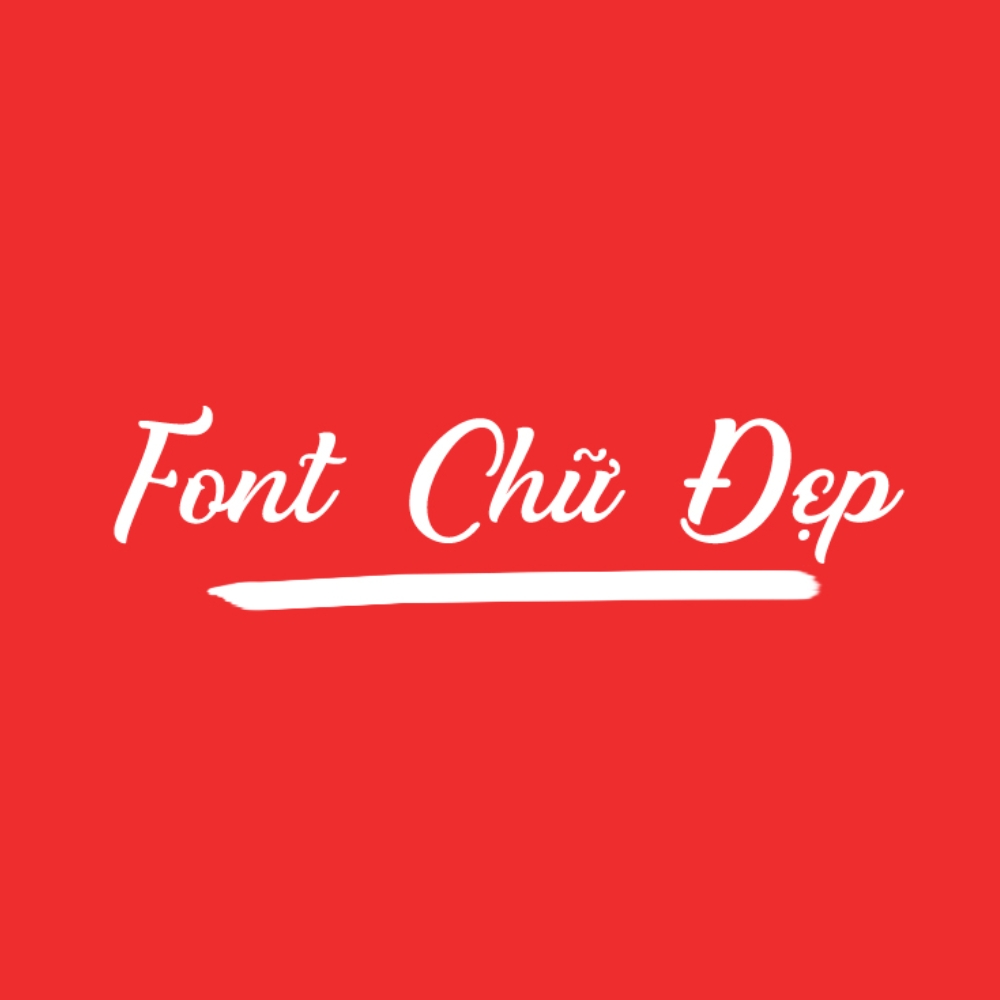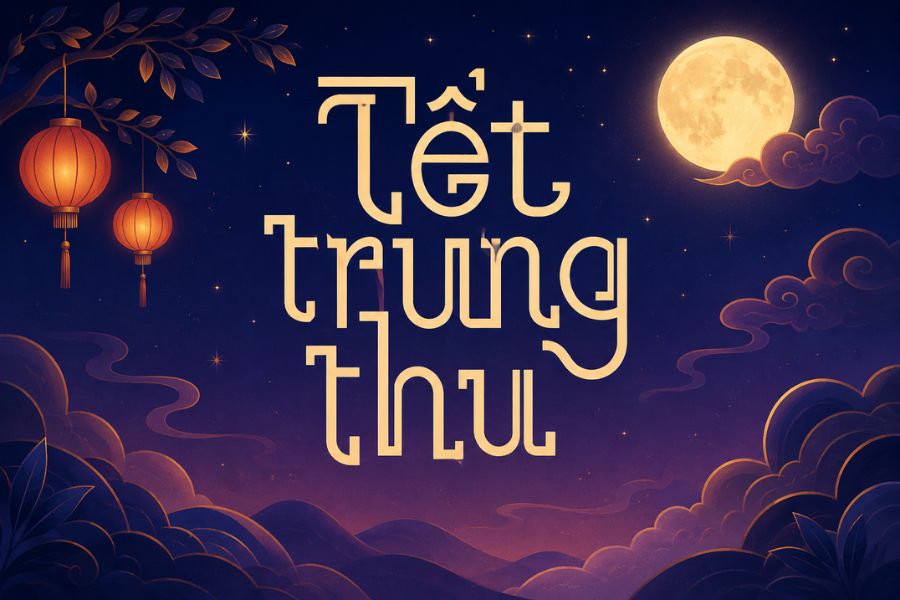
Trong các buổi báo cáo dự án hay thuyết trình ý tưởng kiến trúc, việc lựa chọn font chữ đóng vai trò quan trọng trong việc truyền tải thông tin và duy trì sự chú ý của người xem. Một bộ font chữ đẹp Powerpoint không chỉ giúp trang slide trở nên thẩm mỹ mà còn thể hiện sự chuyên nghiệp và chỉn chu của người trình bày.
Font chữ đẹp Powerpoint – Chìa khóa cho bài thuyết trình lôi cuốn
Khác với các văn bản in ấn thông thường, font chữ thuyết trình đẹp cần đáp ứng được khả năng hiển thị rõ nét từ khoảng cách xa và ổn định trên nhiều thiết bị trình chiếu. Việc sử dụng các bộ font đã được Việt hóa giúp loại bỏ tình trạng lỗi dấu thanh, đảm bảo nội dung tiếng Việt luôn mạch lạc và dễ tiếp nhận. Sự đa dạng từ các dòng font không chân hiện đại đến các dòng script nghệ thuật giúp bạn linh hoạt thay đổi phong cách phù hợp với từng chủ đề báo cáo cụ thể.
Bên cạnh yếu tố dễ đọc, font ppt đẹp còn góp phần định hình cảm xúc cho người xem. Ví dụ, các font chữ vuông vức mang lại cảm giác vững chãi, tin cậy cho các bản kế hoạch thi công, trong khi các font bo tròn lại tạo sự gần gũi cho các dự án cộng đồng. Việc chuẩn bị hồ sơ bài bản với hệ thống kiểu chữ đồng nhất sẽ giúp nâng cao hiệu quả tương tác và thuyết phục chủ đầu tư trong các buổi làm việc trực tiếp.
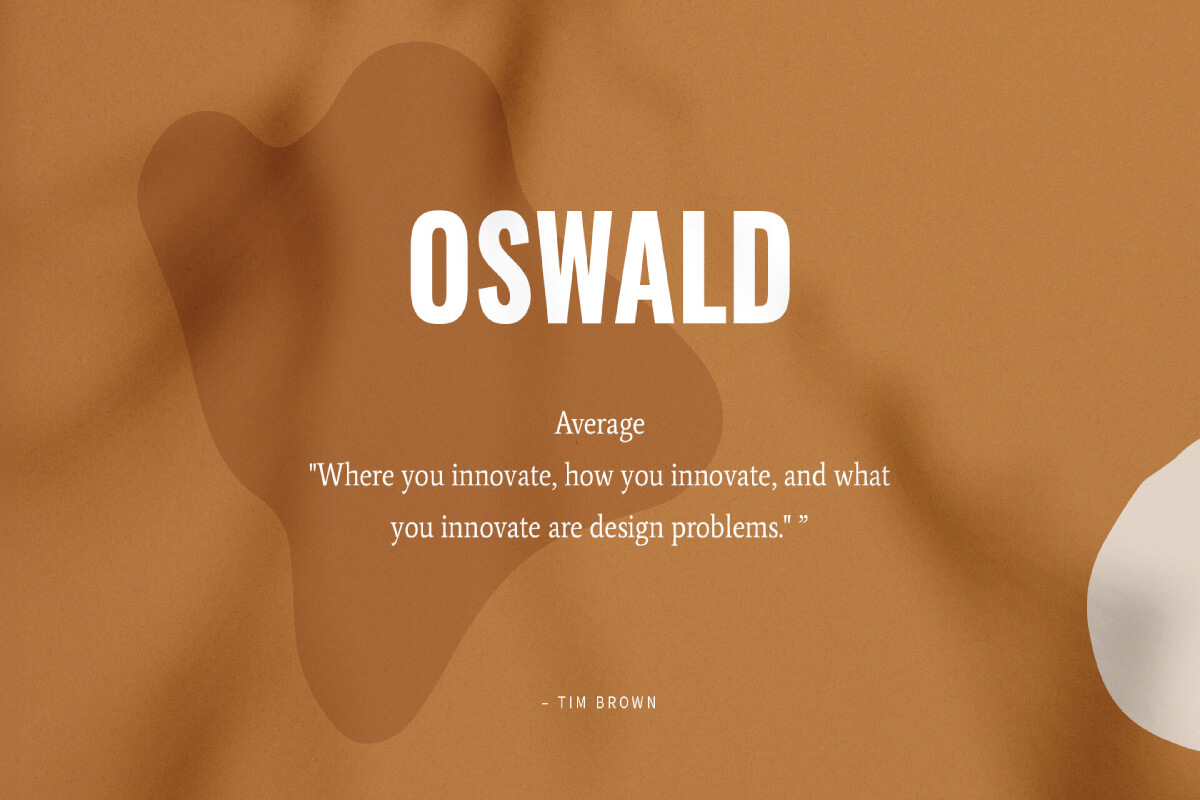
Gợi ý từ chuyên viên: Bạn nên ưu tiên sử dụng các font không chân cho phần nội dung chi tiết vì chúng giúp mắt người nhìn dễ dàng theo dõi thông tin trên màn hình trình chiếu. Các font có chân hoặc font nghệ thuật chỉ nên dùng cho tiêu đề chính để tạo điểm nhấn thị giác.
03 Ứng dụng font chữ thuyết trình đẹp trong báo cáo dự án kiến trúc
Nhờ vẻ ngoài khoa học và dễ tiếp nhận, việc lựa chọn font chữ đẹp cho Powerpoint mang lại giá trị thực tế cao trong quá trình làm việc với khách hàng và đối tác:
- Hồ sơ năng lực doanh nghiệp: Thể hiện tầm nhìn và kinh nghiệm của đơn vị thông qua cách trình bày thông tin mạch lạc, đồng bộ về kiểu chữ, giúp xây dựng niềm tin từ cái nhìn đầu tiên.
- Thuyết minh phương án kiến trúc: Sử dụng font chữ thuyết trình đẹp để trình bày các ưu điểm của giải pháp nhà lắp ghép, văn phòng container giúp khách hàng nhanh chóng nắm bắt các đặc tính về vật liệu và công năng.
- Báo cáo tiến độ và dự toán công trình: Giúp các bảng biểu và con số trở nên minh bạch, rõ nét, hạn chế tối đa việc nhầm lẫn thông tin khi chủ đầu tư theo dõi ngân sách và kế hoạch triển khai dự án.
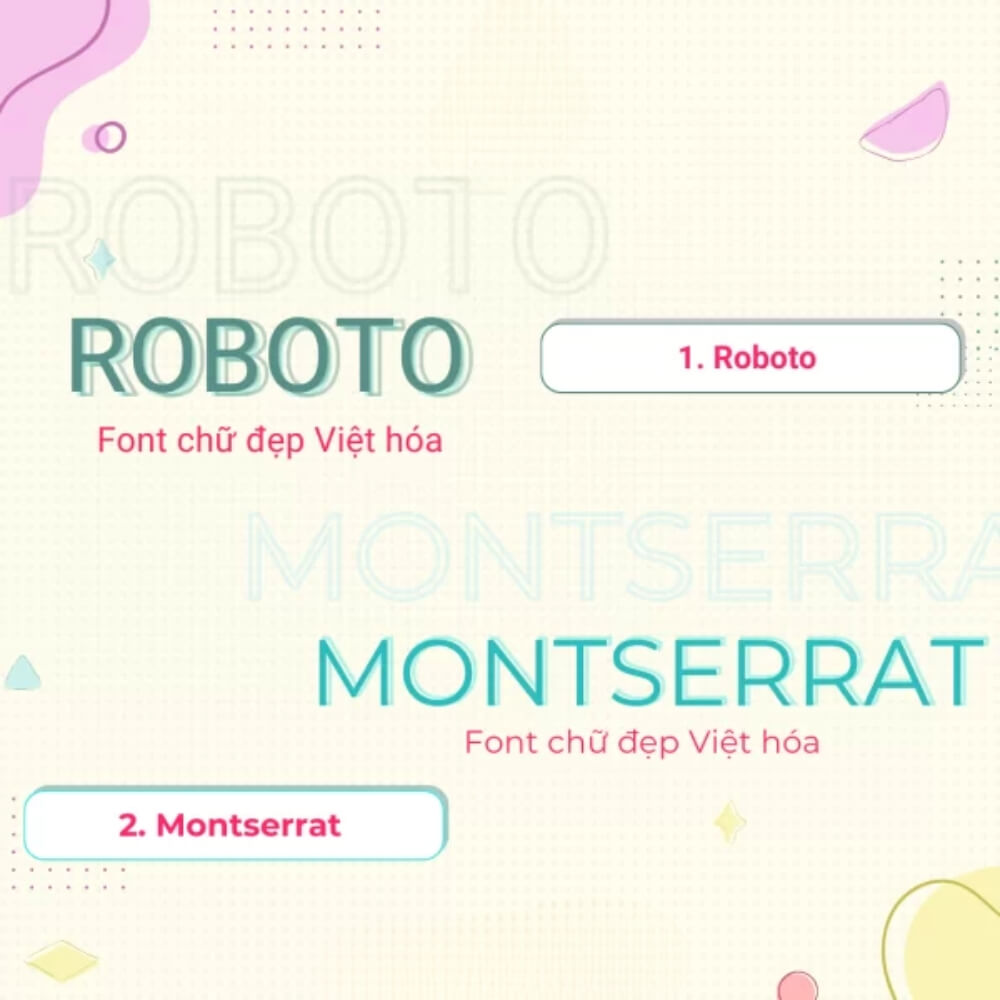
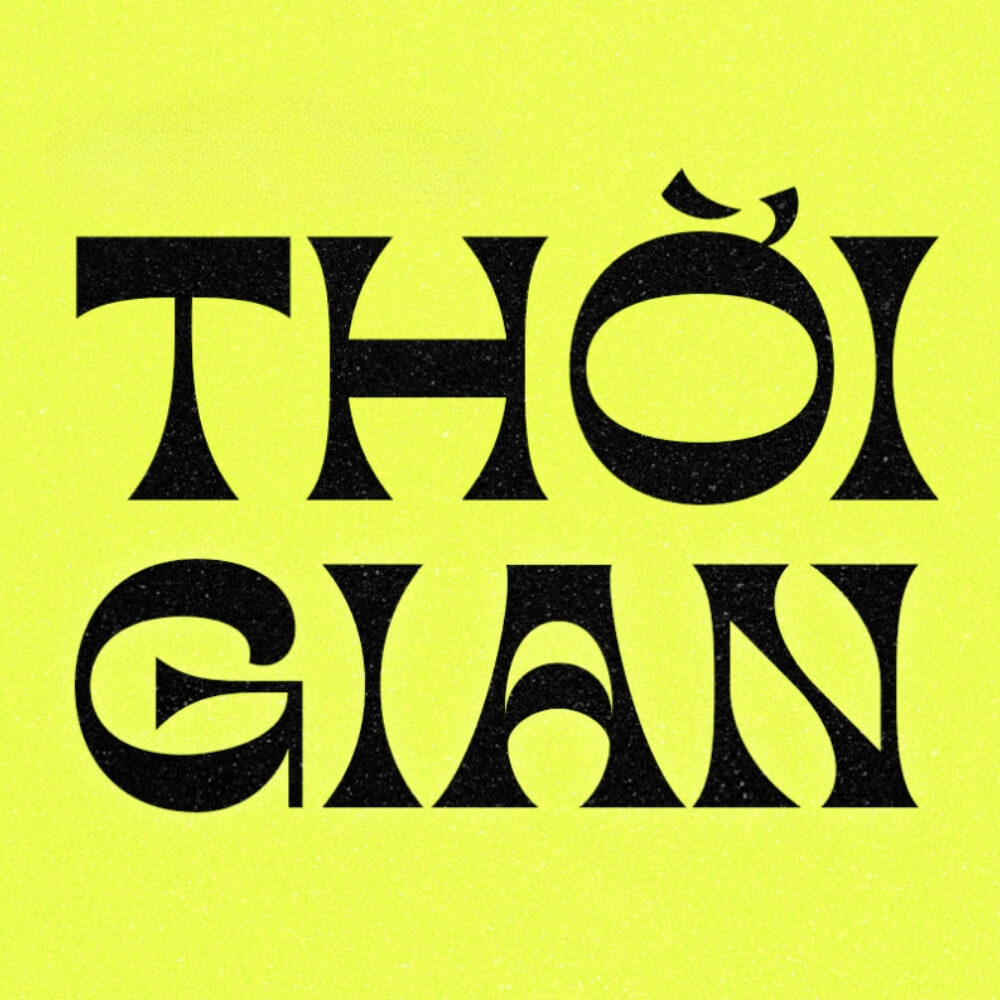
03 Lưu ý khi sử dụng font chữ thuyết trình đẹp để đạt hiệu quả cao
Để font chữ ppt đẹp phát huy hiệu quả mà không làm người xem cảm thấy rối mắt, bạn nên lưu tâm một số kinh nghiệm sau:
- Kiểm soát số lượng font chữ: Trong một bài thuyết trình, chỉ nên sử dụng tối đa 2-3 kiểu font khác nhau để duy trì tính đồng nhất. Việc lạm dụng quá nhiều kiểu chữ sẽ khiến Slide trở nên lộn xộn và thiếu chuyên nghiệp.
- Đảm bảo kích thước chữ hợp lý: Với nội dung chính, cỡ chữ nên từ 24pt trở lên để đảm bảo mọi người trong phòng họp đều có thể đọc được. Tiêu đề cần có kích thước nổi bật hơn để phân cấp thông tin rõ ràng.
- Chú ý độ tương phản màu sắc: Bạn nên đặt chữ trên nền có độ tương phản cao (ví dụ chữ tối màu trên nền sáng hoặc ngược lại). Tránh đặt chữ lên các hình ảnh có quá nhiều chi tiết gây nhiễu, làm giảm khả năng nhận diện mặt chữ.